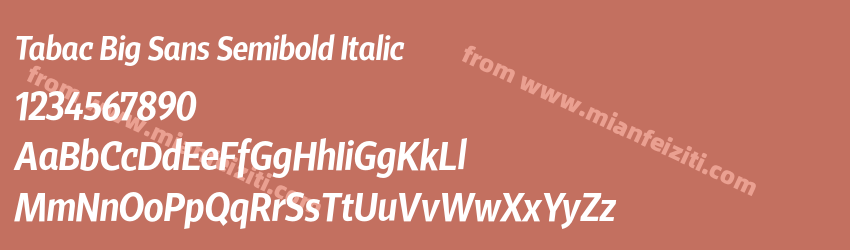
Tabac Big Sans Semibold Italic
字体名称: Tabac Big Sans Semibold Italic
Postscript名称: TabacBigSans-SemiBoldIt
字体字重: SemiBold Italic
本款“Tabac Big Sans Semibold Italic”是一款书写很新颖的字体,字体大方,适合各种设计作品使用!欢迎下载!